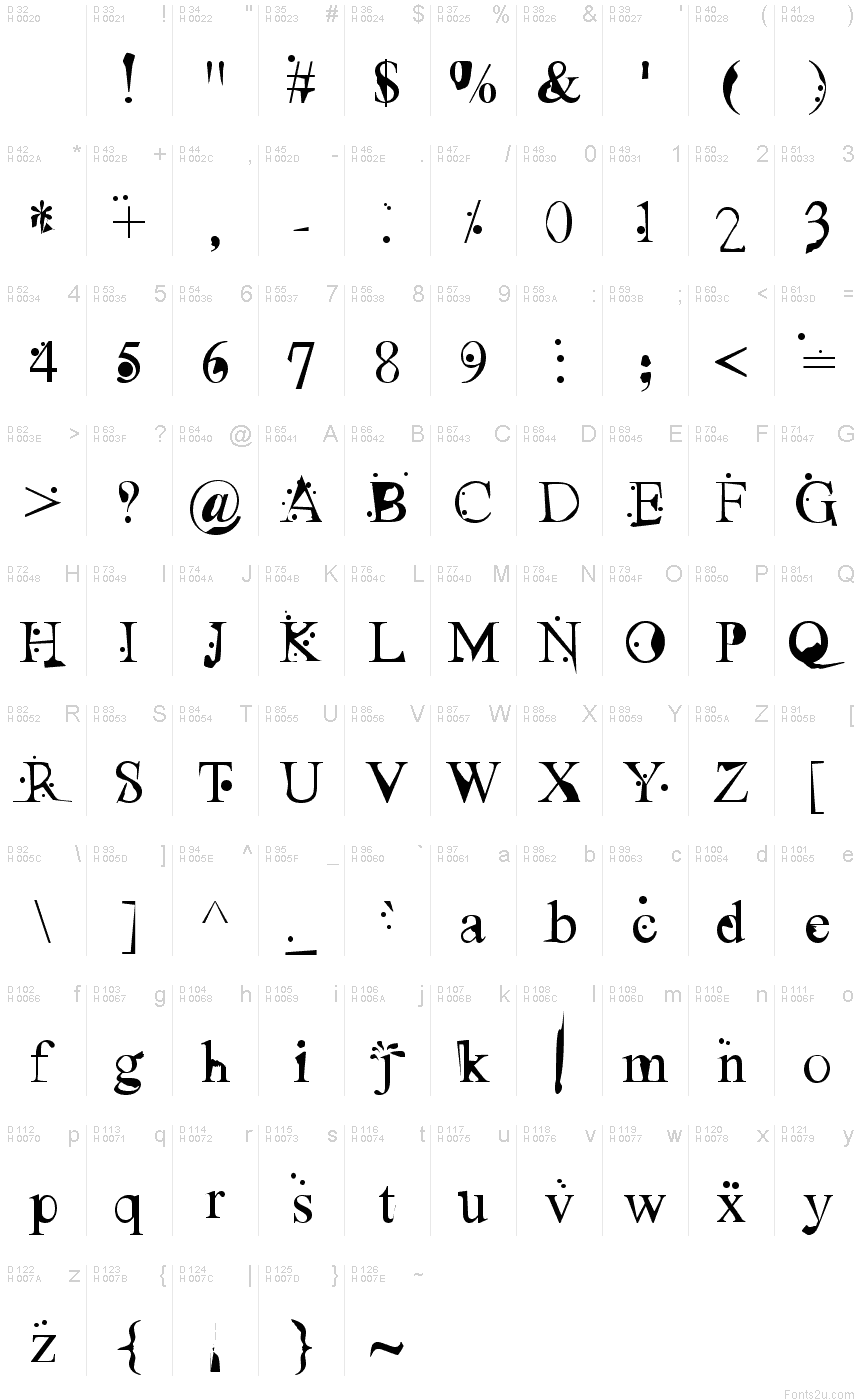
Ugly Face, stworzony przez Jasona i Grega, to darmowy, zniekształcony krój szeryfowy typu display o celowo niezgrabnym, gotyckim klimacie rodem z baśni. Litery łączą wdzięczne, staromodne krzywizny z nagłymi, nietrafionymi akcentami – napuchnięte „g”, poszarpane „y” i wysoki, kleksowaty kres, które nadają całemu krojowi psotnego, a nie uporządkowanego charakteru.
Świetnie sprawdzi się w tytułach plakatów, okładkach książek, nagłówkach zinów, grafikach na Halloween i krótkich projektach brandingowych, w których potrzebujesz darmowego fontu o literackim wyglądzie z nutką przekory. Używaj go w krótkich nagłówkach, kartach tytułowych czy dużych inicjałach, gdy chcesz zachować tradycję szeryfów, pozwalając jednocześnie, by detale stały się dziwne.
Ugly Face, by Jason & Greg. It's ugly.